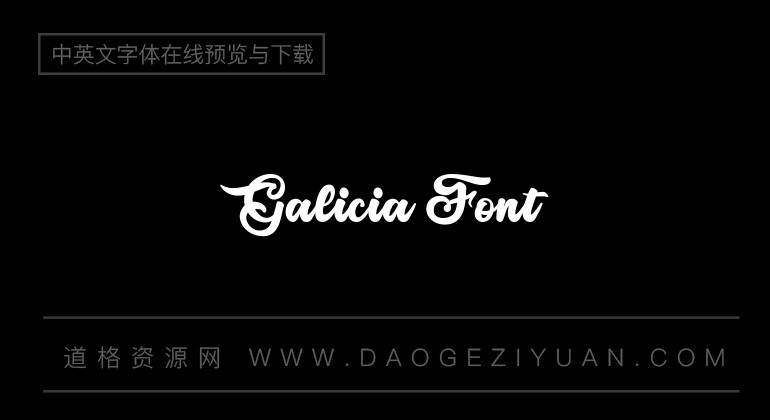
Galicia Font 是一种现代风格的字体,由设计师 João Symington 创建。这种字体有着独特的线条和流畅的曲线,适用于设计海报、标志、标签和标题等宣传设计。Galicia Font 可以通过 Google Fonts 网站免费下载和使用。该字体的特点是字母间距较宽,字母的笔画粗细变化明显,整体呈现出一种时尚、现代的感觉。内容介绍
Galicia Font是一款非常不错的手写艺术字体,具有很好的视觉感,适合于文化类的宣传设计、商业类品牌的广告和产品包装设计以及个性化文字排版等较多场景。